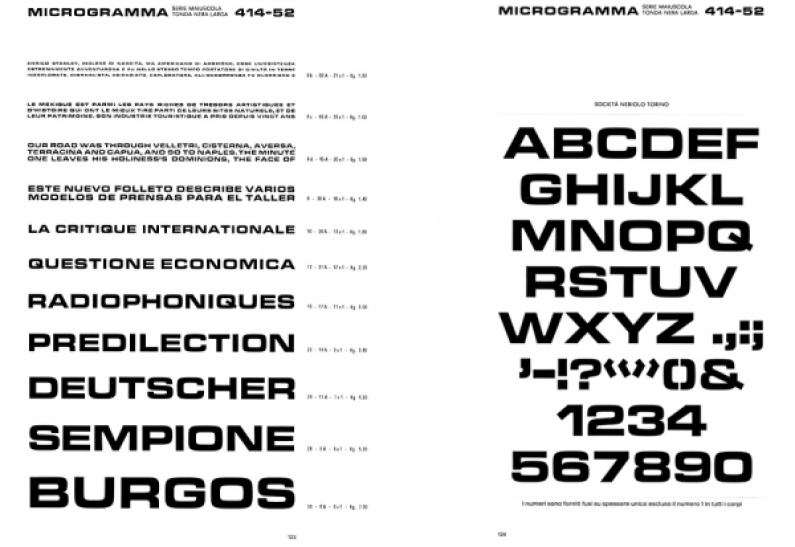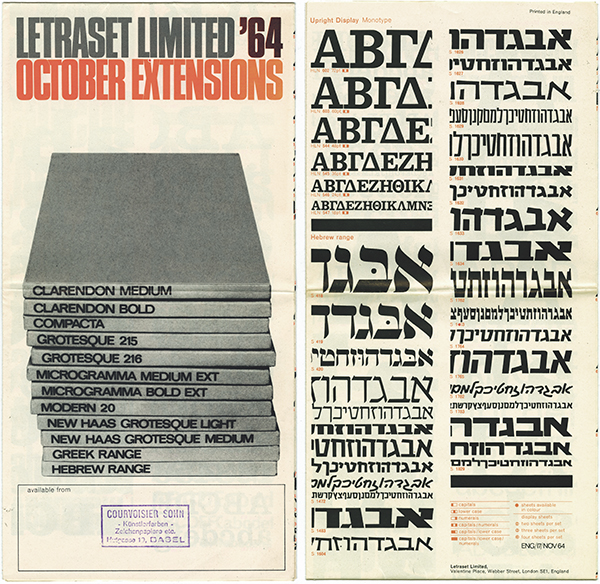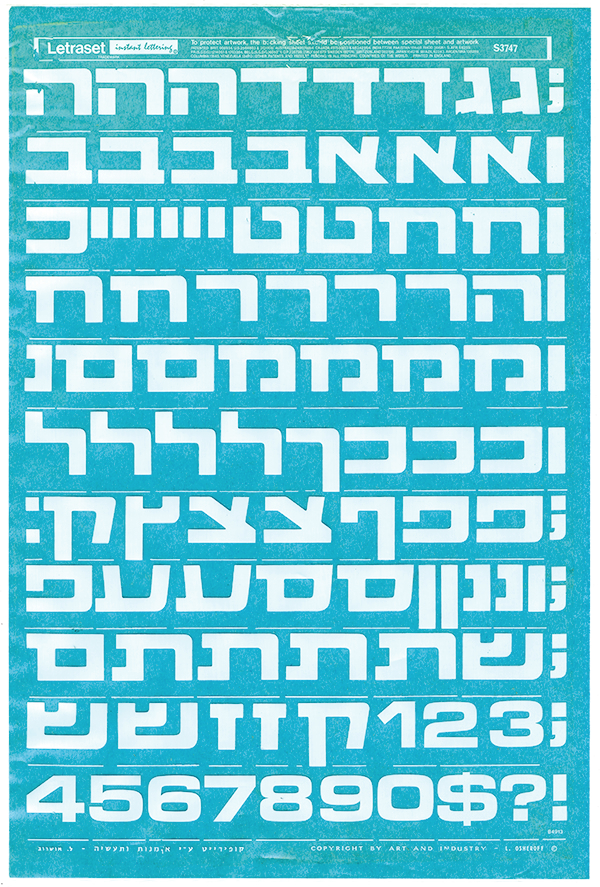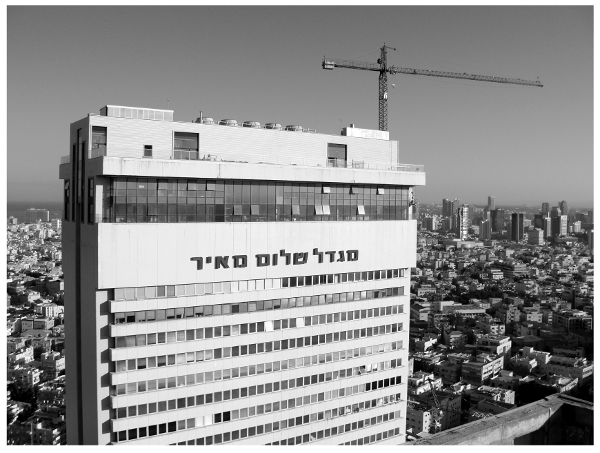
‹Microgramma Hebräisch› & Letraset
Die ‹Microgramma› wurde 1952 von Alessandro Butti und seinem Assistenten Aldo Novarese für die Schriftgiesserei Nebiolo in Turin geschaffen. Sie wurde von Nebiolo in fünf Schnitten als Titelschrift für den Handsatz produziert. Anfänglich als reine Grossbuchstabenschrift konzipiert, schuf Novarese 10 Jahre später – mittlerweile einer der bedeutensten Schriftgestalter Italiens[1] – zusätzlich Kleinbuchstaben zur ‹Microgramma› und nannte die so ergänzte Schrift ‹Eurostile›. Der Schriftgestalter verstand sein Werk als typografischen Ausdruck einer von Fortschrittsoptimismus geprägten Zeit:
«Trough its compact and square lines Eurostile most efficiently expresses modernity and synthesizes the tendency towards a functionalism that solves many aesthetic problems and gives a modern and typical appearance to a printed page. Its outline is already familiar and unconsciously present whenever we look at a television set which recalls to mind the typical shape of an ‹O›. The same impression we get looking at a series of windows of fast moving vehicles.»[2]
Die ursprünglich für den Bleisatz geschaffenen Schriften verbreiteten sich nicht zuletzt auch dank der Firma Letraset Ltd., die sie in ihrem Katalog aufgenommen hatte. Letraset hatte 1961 unter dem Namen «instant lettering» ein Prinzip zur trockenen Übertragung von auf Folie gedruckten Transferschriften entwickelt, dass dem Unternehmen in kurzer Zeit grossen Erfolg bescherte. Bereits 1963 wurde die Firma an der Londoner Börse gelistet und ihre Anreibebuchstaben weltweit in 70 Ländern vertrieben.[3]
Letraset Limited '64 October Extensions (Faltblatt, recto/verso)
Bald wurde der Letraset-Schriftenkatalog um nicht-lateinische Schriften erweitert und Ende 1964 erschien im Rahmen der «October Extensions» neben griechischen auch zehn hebräische Schriften – mit einer Ausnahme allesamt originäre Entwürfe, inspiriert von der zeitgenössischen israelischen Werbegrafik.[4] Über die Gestalter/innen ist nichts genaueres bekannt. Es darf aber vermutet werden, dass beim Zustandekommen dieser ersten Hebräischen Letraset-Kollektion Leo und Tamar Osheroff eine Rolle gespielt haben. Das Paar gründete 1964 in Israel «Arta», eine Firma zum Vertrieb von Büro- und Künstlerbedarf mit Läden in Tel Aviv und Haifa.[5] Auf einer Reihe dort verkaufter Bögen mit hebräischen Letraset-Schriften wird Leo Osheroff als Rechteinhaber genannt.
Unter den 1964 von Letraset publizierten Schriften findet sich auch eine hebräische Version der ‹Microgramma›, der sich offenbar an einem entsprechenden Entwurf eines Tel Aviver Herstellers von Kunstoffschriften für den Plakatdruck orientiert.[6] Die Letraset-Schrift entspricht dem fetten und breiten Schnitt des Originals und verwendet auch die entsprechenden Ziffern, wobei hier, anders als beim Original, die Strichstärken nicht ganz übereinstimmen. Die ‹Microgramma Hebräisch› überträgt die zentralen Gestaltungsprinzipien des lateinischen Vorbilds relativ frei auf die Grundformen der 27 hebräischen Lettern. Aufgrund der Unterschiede zwischen den beiden Schriftsystemen tritt bei der hebräischen Version gerade das für das ursprüngliche Schriftbild so bestimmende abgerundete Rechteck – das Novarese u.a. auf die Form des klassischen Fernsehbildschirms bezieht – weitgehend in den Hintergrund. Dennoch entspricht der Gesamteindruck der Schrift dem der ‹Microgramma›.
Verwendung fand die ‹Microgramma Hebräisch› in Israel unter anderem auch bei der Beschriftung des 1965 feriggestellten Shalom Tower (Migdal Shalom Meir) in Tel Aviv. Das 34-stöckige Hochhaus war lange Zeit das höchste Gebäude des Nahen Ostens. Errichtet wurde es an Stelle des dafür abgerissenen Herzl-Gymnasiums aus dem Jahr 1909. Seine Geschichte macht das Hochhaus zum Symbol einer ebenso optimistischen wie rücksichtslosen Moderne.[7]
Beschriftung «Migdal Shalom Meir», Tel Aviv
[1] Vgl. «Aldo Novarese», Index Grafik, 25.04.2016.
[2] Aldo Novarese: «Eurostile, a Synthetic Expression of Our Times», Pagina, Nr. 4 (1964).
[3] Vgl. Jane Lamacraft: «Rub-down revolution», Eye Magazine, Nr. 86 (2013).
[4] Ein späterer israelischer Katalog nennt die Namen «Etz Atik», «Zwiah», «Polly», «Rahel» , «Shmuel», «Mizrahi», «Microgramma», «Grotesque», «Armon» und «Meurav». Vgl. Arta/Letraset Reference Book (1988).
[5] Im Arta-Hauptgeschäft an der Nahalat Binyamin Strasse 83 in Tel Aviv findet sich heute noch eine grosse Auswahl von Letraset-Bögen mit lateinischen, hebräischen, kyrillischen und arabischen Schriften.
[6] Vgl. Katalog Otiot Sadeh (1955, ca.).
[7] Vgl. Esther Zandberg: «September 9, 1965: Tel Aviv’s Shalom Tower Inaugurated», Haaretz, 16.06.2016.